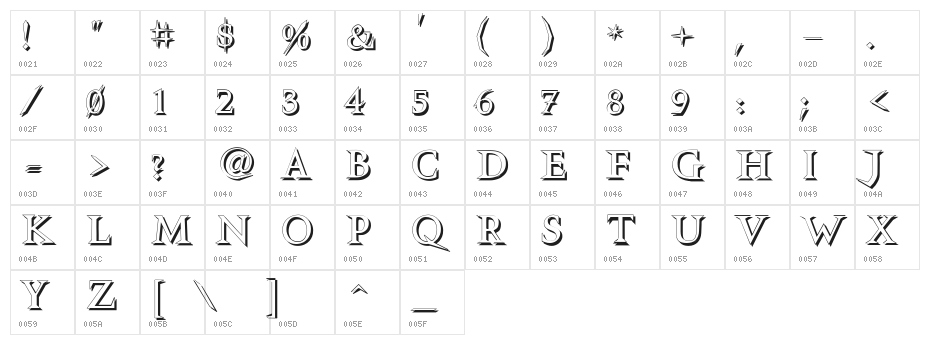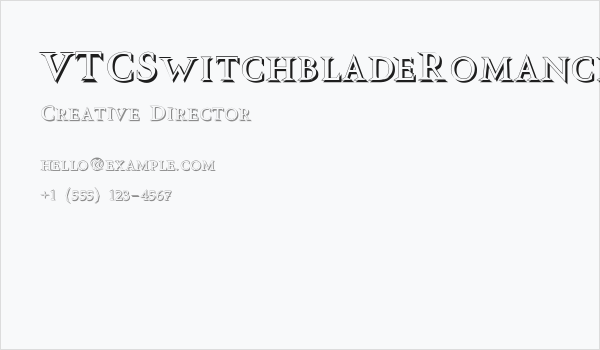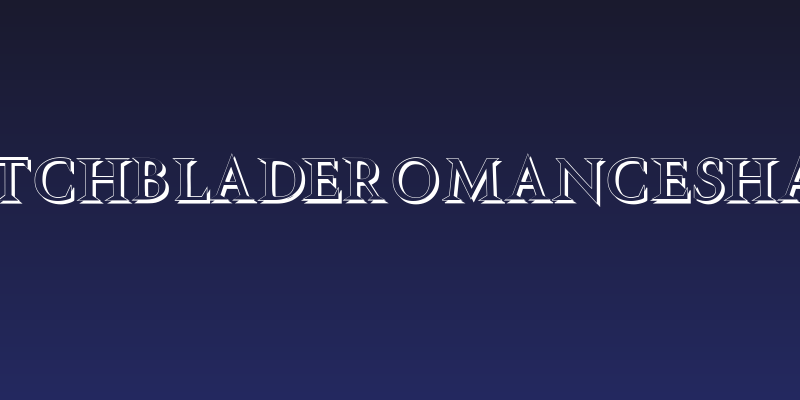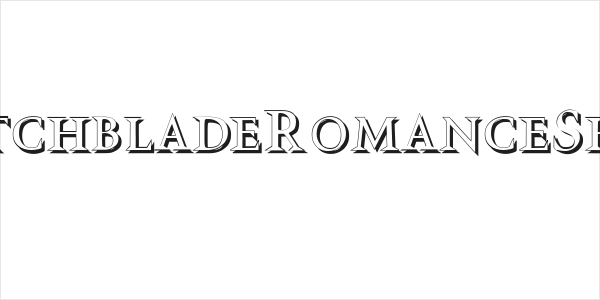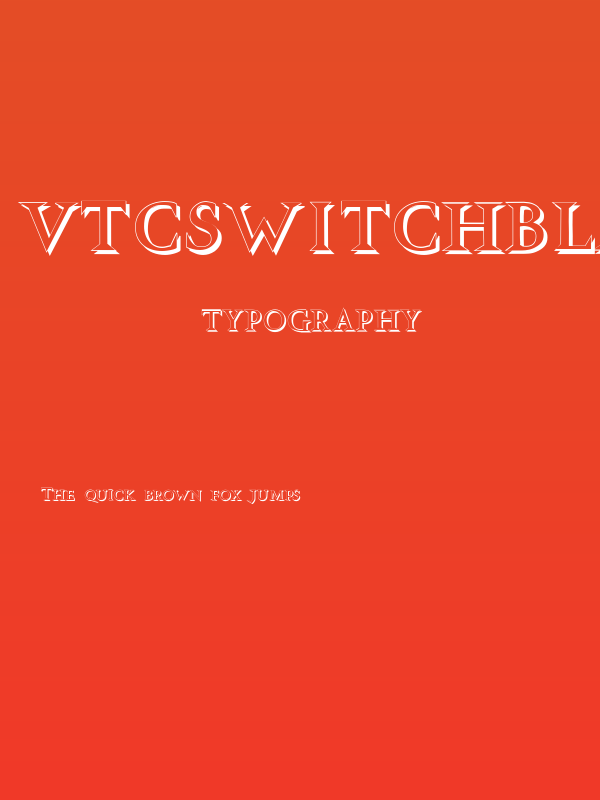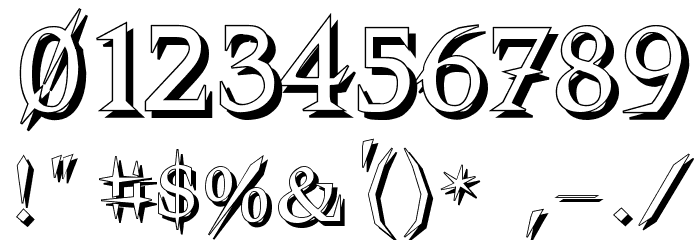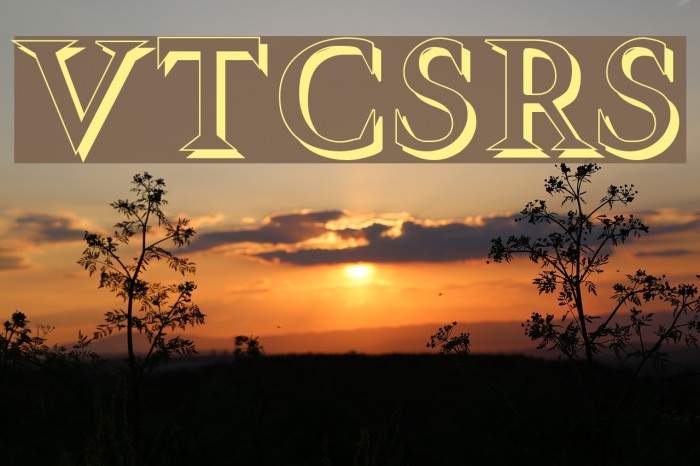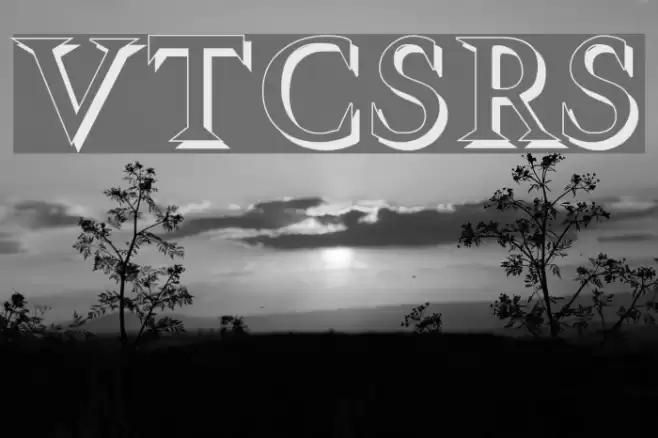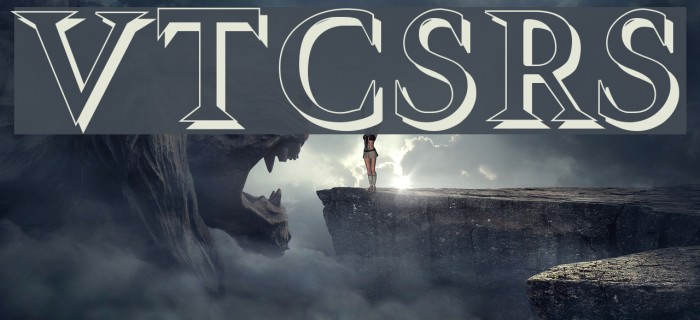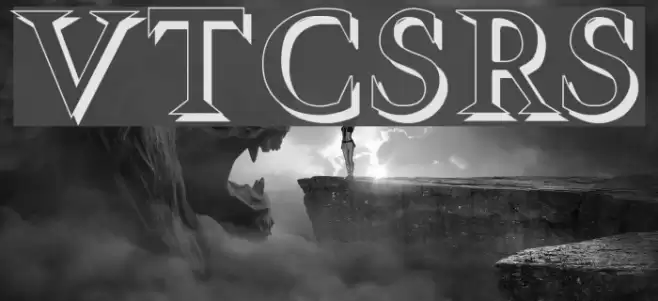
VTCSwitchbladeRomanceShadowed Font
✎ Outline
| 名前 | VTCSwitchbladeRomanceShadowed |
| ウェイト | Shadowed |
| カテゴリ | Outline |
| おすすめプロジェクト | Ideal for posters, logos, album covers, and any design needing a bold, vintage look. |